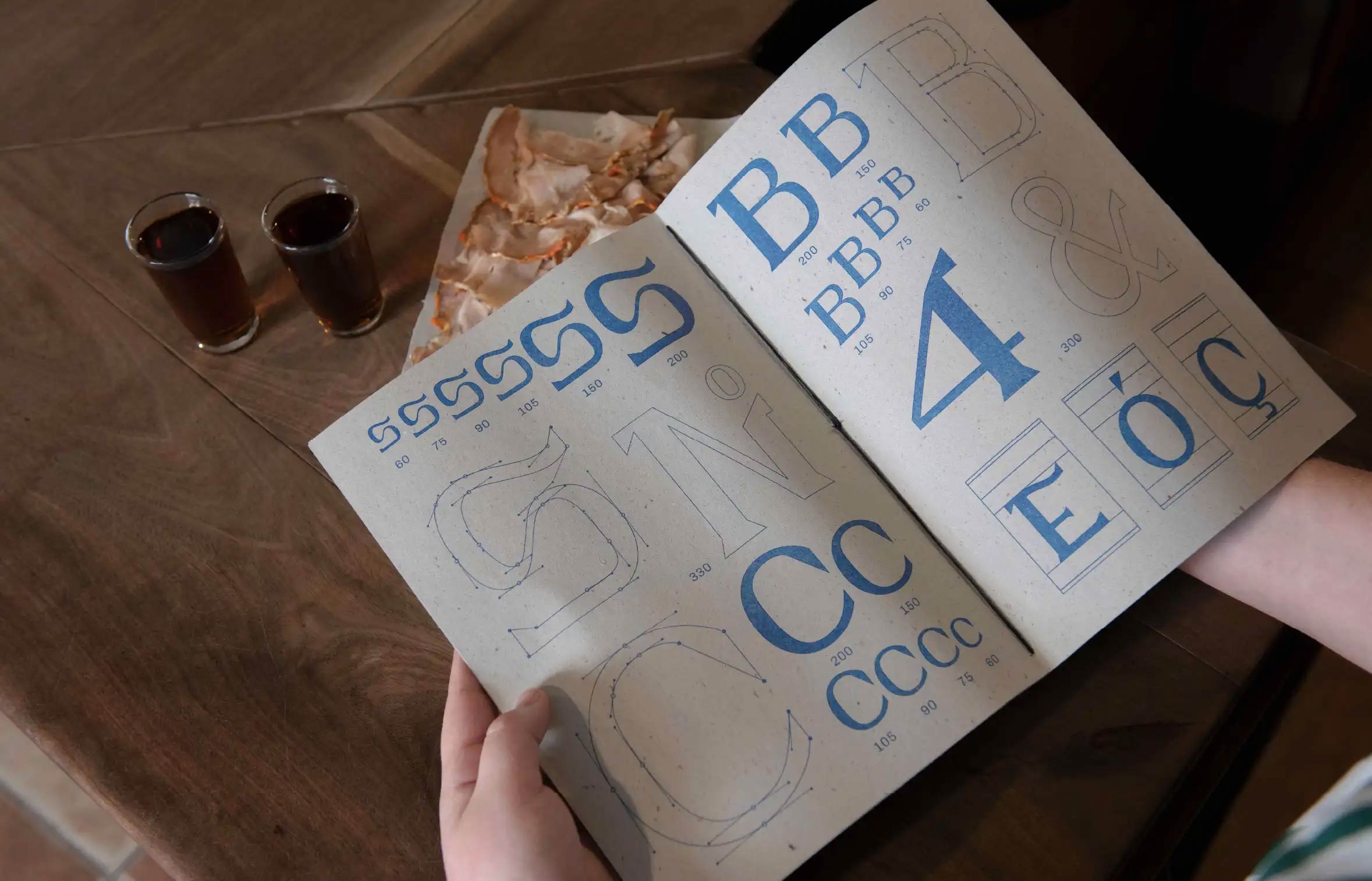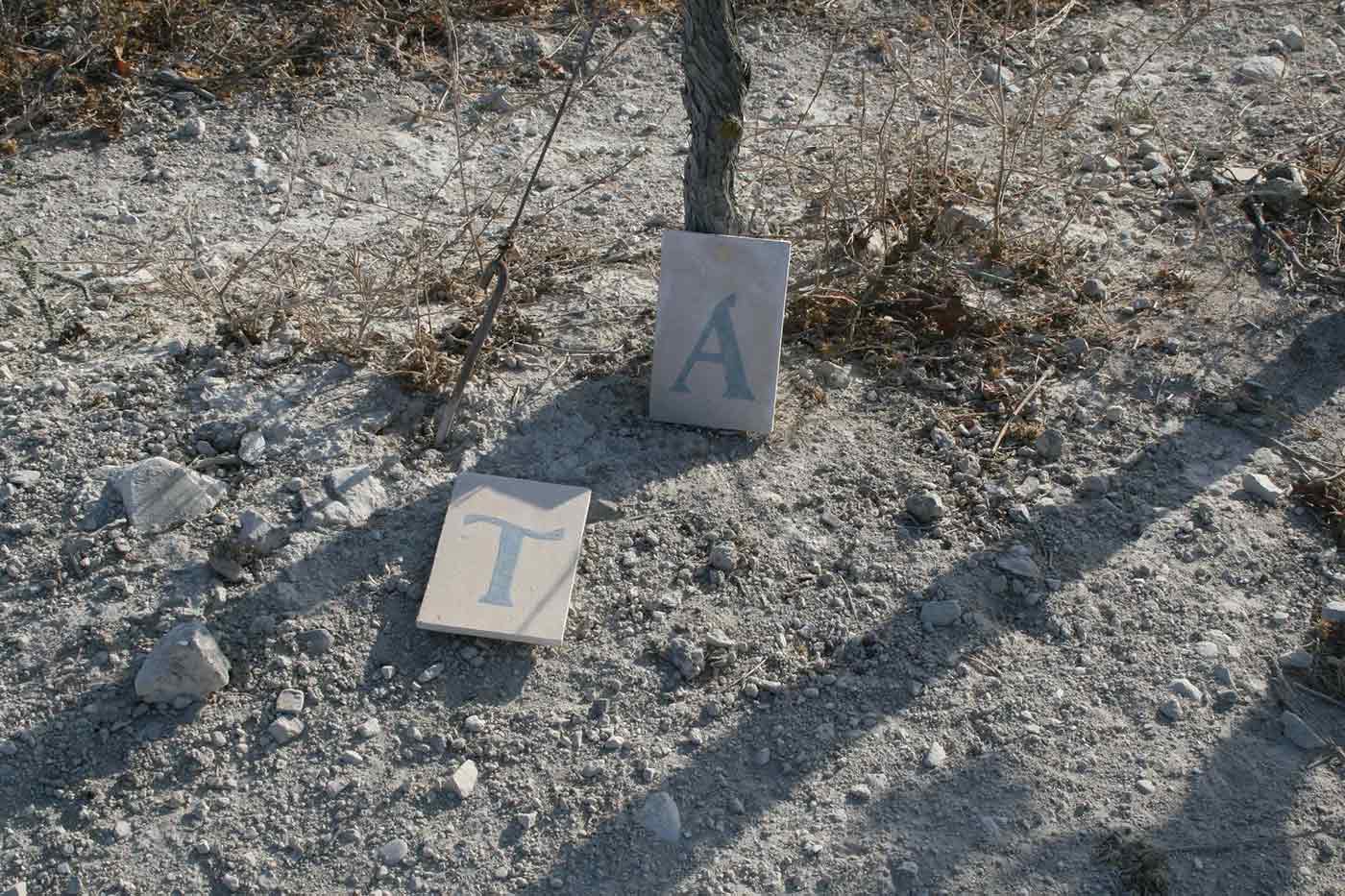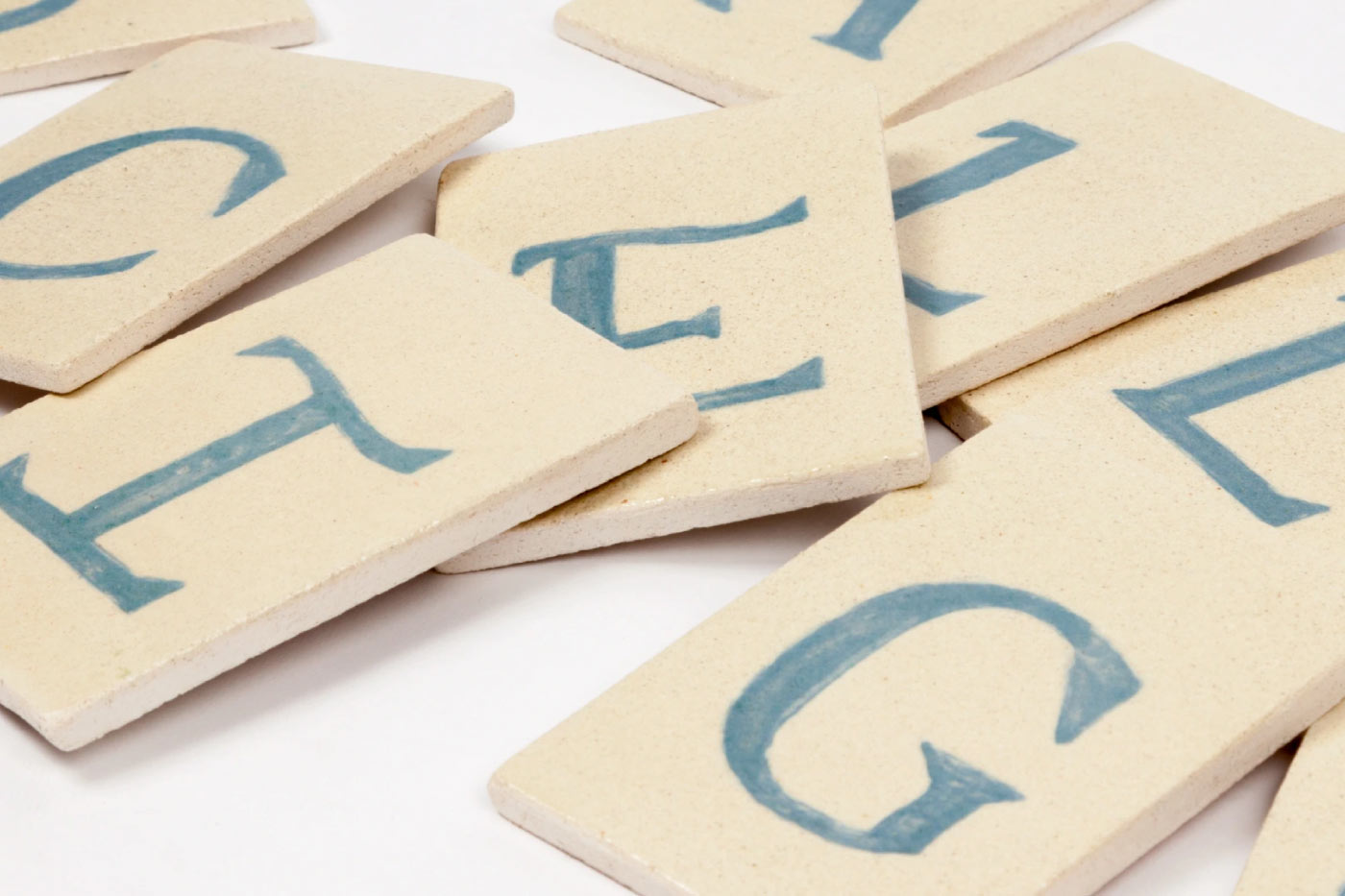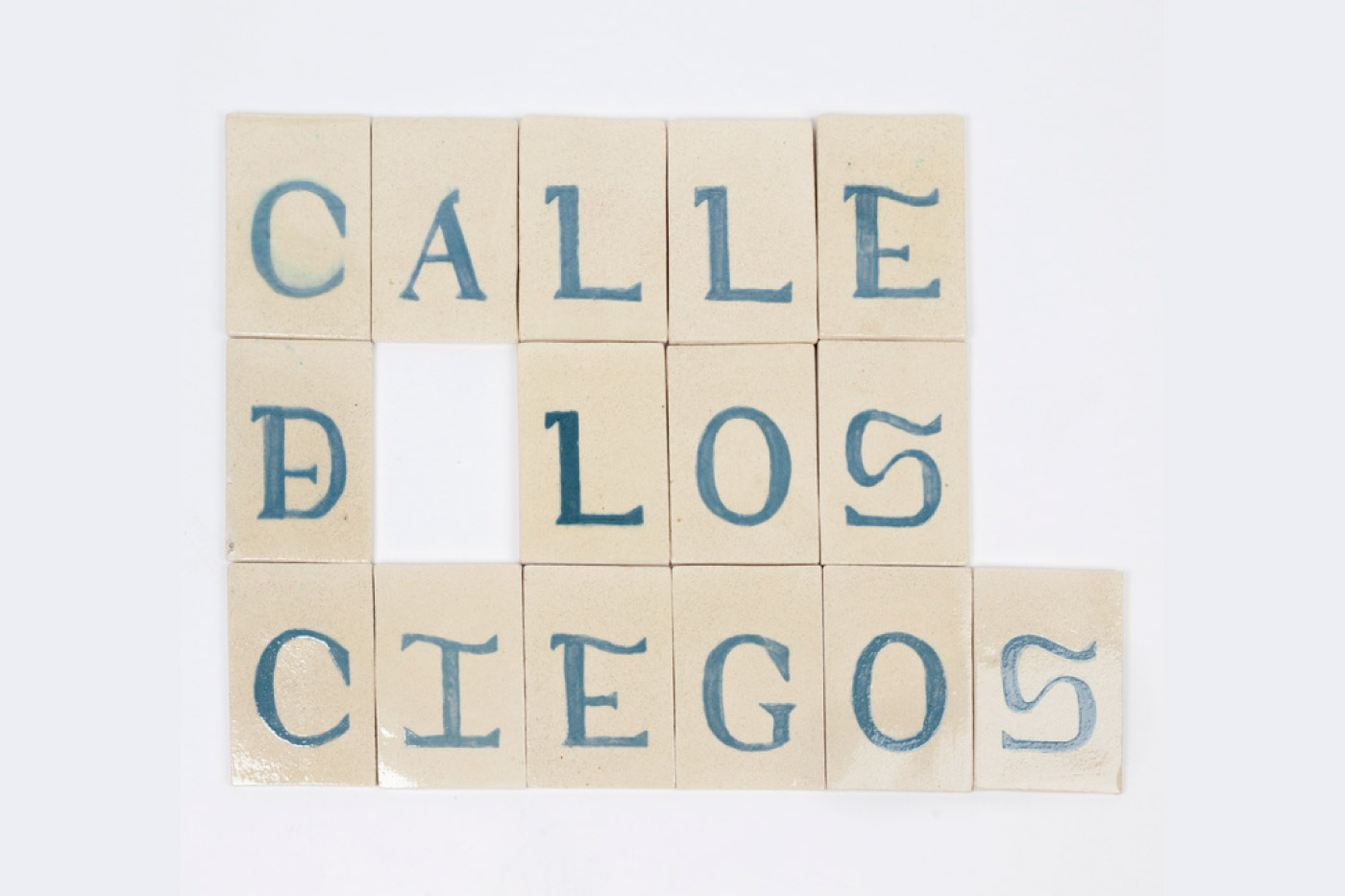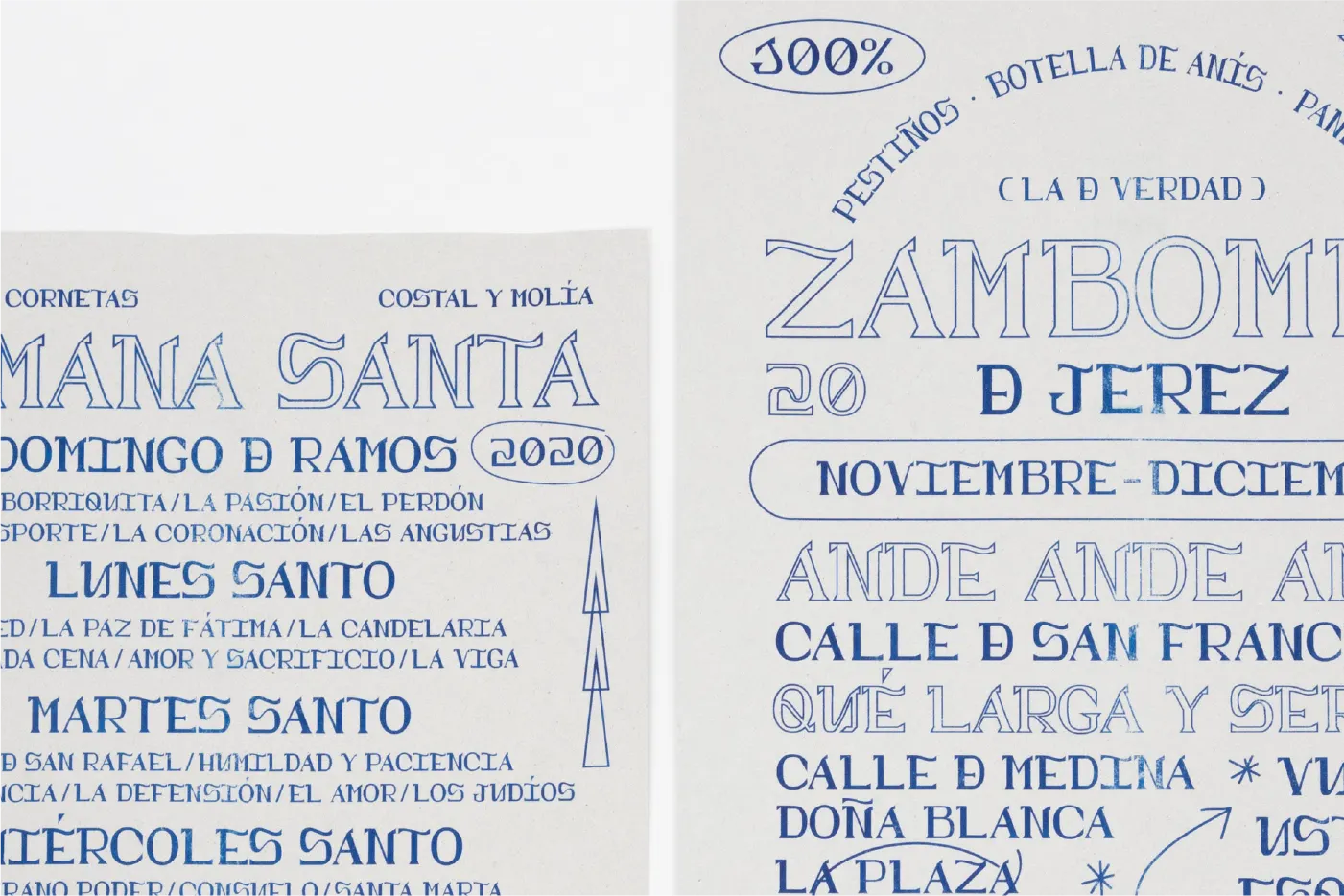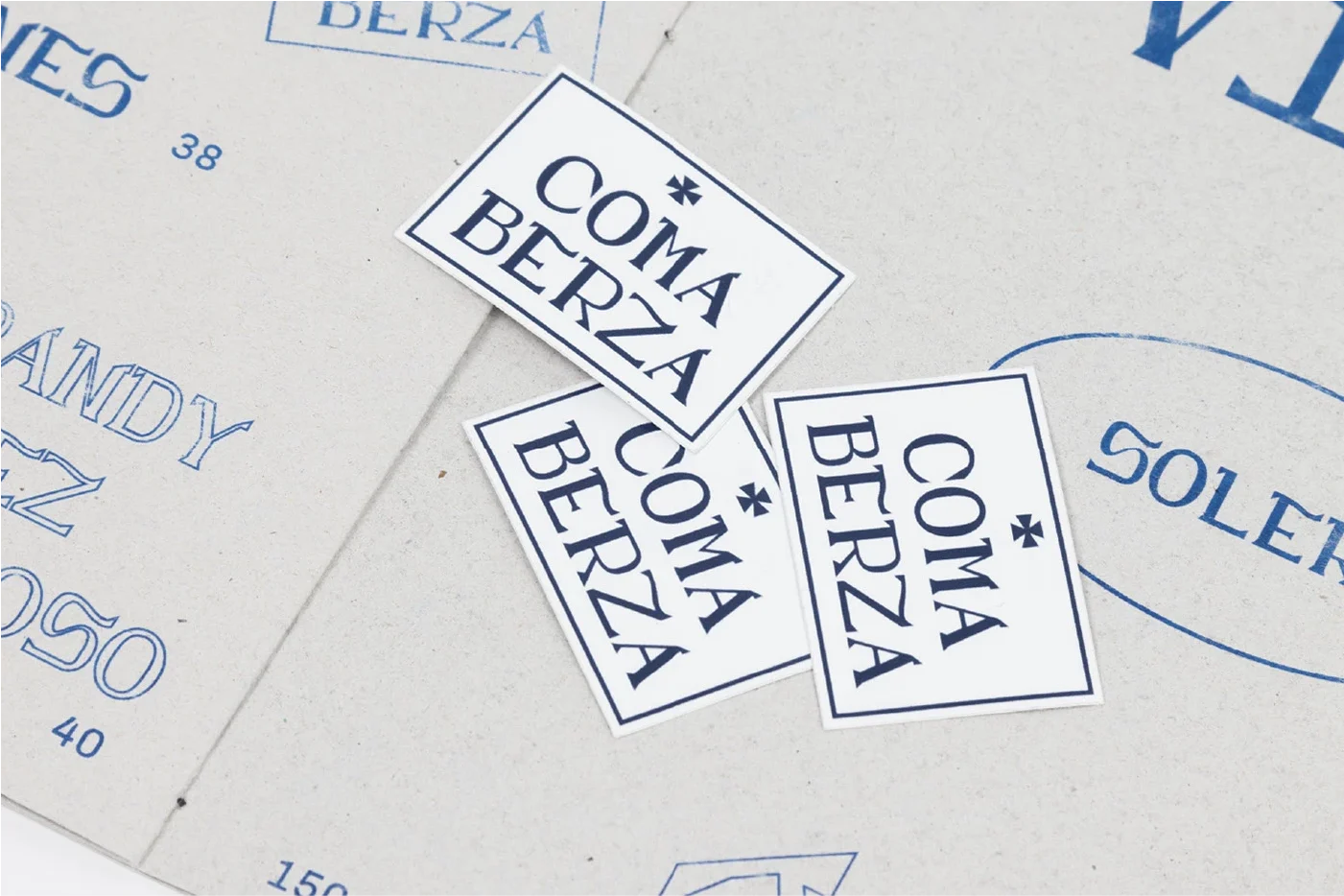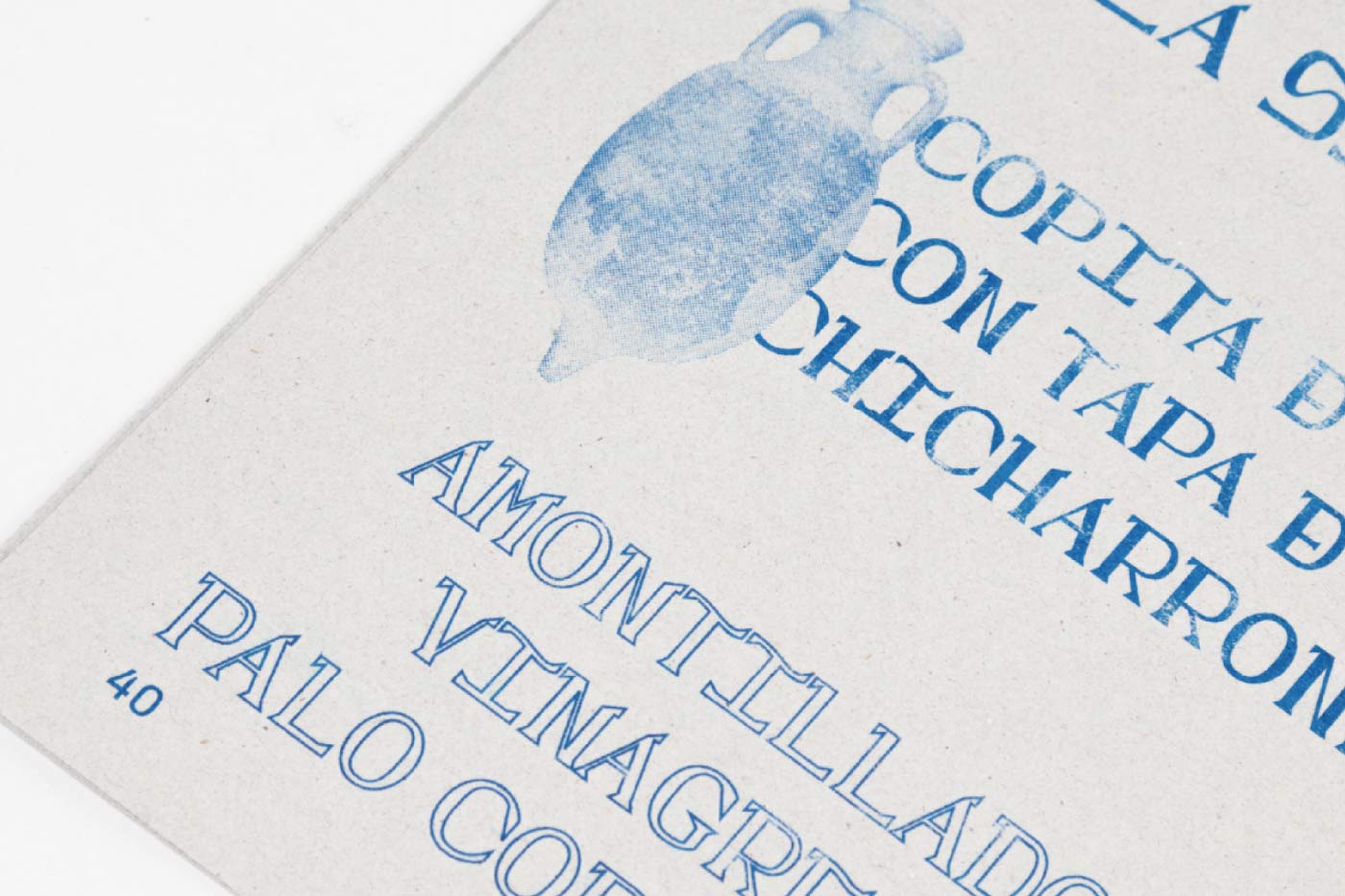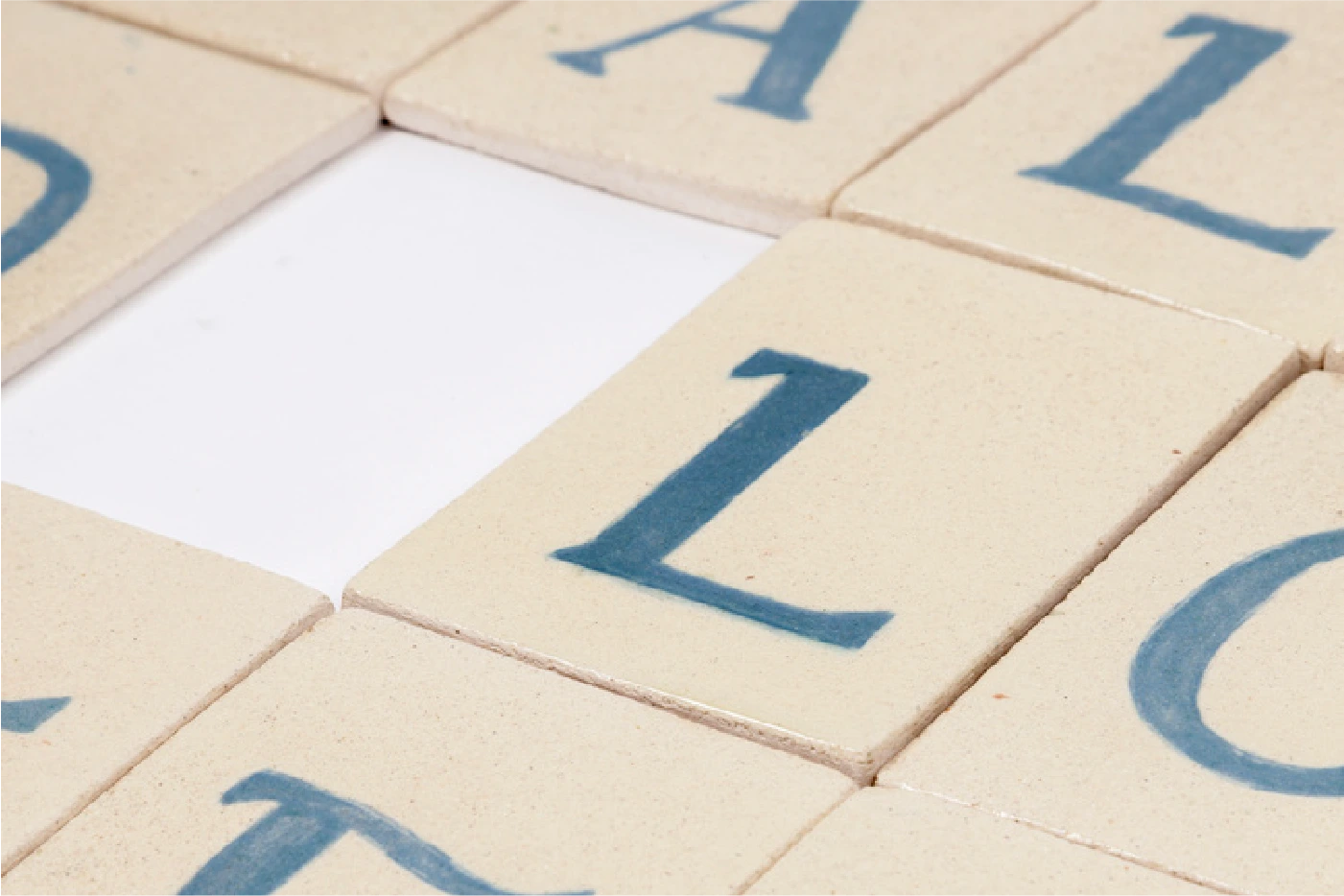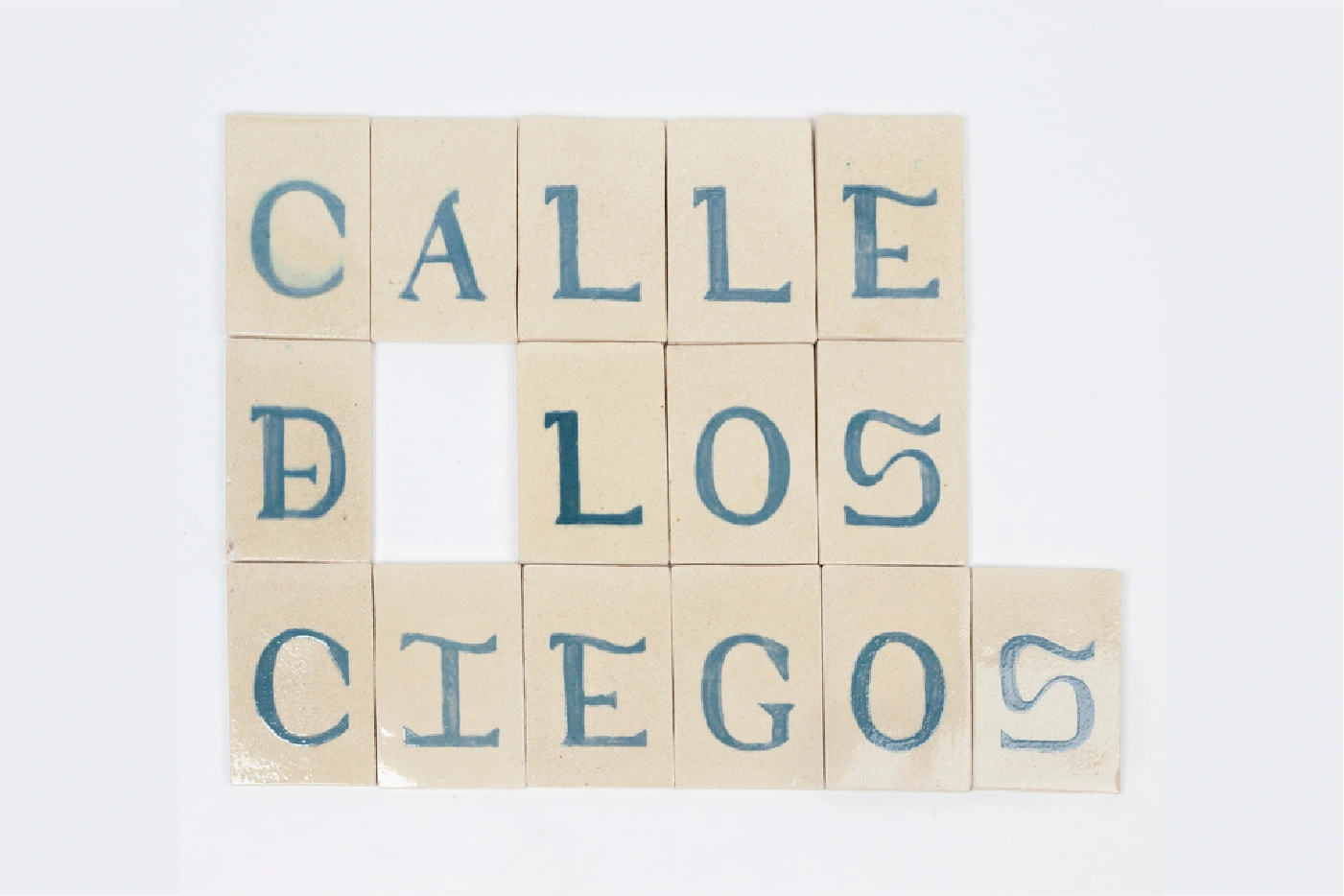
ASTA
La tipografía de Jerez
ASTA
La tipografía de Jerez
cultura e historia para la identidad de Jerez
Rescate arqueológico y diseño de tipos
Asta es una tipografía mono espaciada de carácter decorativo, nacida de la piedra y de la azulejería fina. En concreto, su diseño se fundamenta en el estudio de las lápidas funerarias romanas halladas en el yacimiento de Mesas de Asta. Por lo tanto, el proyecto nace con el fin de volver al origen para finalmente transformarse en una herramienta digital contemporánea. Además, logramos una tipografía con identidad propia.
Desde este Despacho de Tipos, no solo fundimos letras, sino que también recuperamos el sentimiento de pertenencia a través de la gráfica. De este modo, Asta actúa como un puente histórico diseñado para potenciar la cultura de Jerez de la Frontera, respondiendo así a las necesidades de señalética con un lenguaje tanto local como universal . Por esta razón, nos enorgullece que nuestra labor se hable en reconocidos certámenes como Laus y Selekted
Del soporte digital a la cerámica tradicional
En cuanto a su versatilidad, Asta se despliega en dos vertientes: una versión digital y una versión impresa en cerámica. Esta última, recupera los antiguos oficios de rotulación, en cerámica, para que la tipografía se integre en el paisaje urbano como un elemento vivo de nuestra arquitectura. Además, esta dualidad permite que el diseño sobreviva y dialogue con diferentes soportes.
Papel de estraza y tabancos
Fieles a la idea de lo cercano, el espécimen de Asta se despacha en papel de estraza, especialmente por su carga histórica. Debido a que este material humilde está ligado al comercio tradicional y a la solera de los tabancos, la tipografía se acaba conviertiendo en un objeto táctil. En definitiva, se trata de una evolución gráfica que rescata elementos olvidados para convertirlas en identidad.
| Origen: Inscripción epigráfica (Mesas de Asta) y azulejos calles s.XVIII | Distribución: Despacho de Tipos |